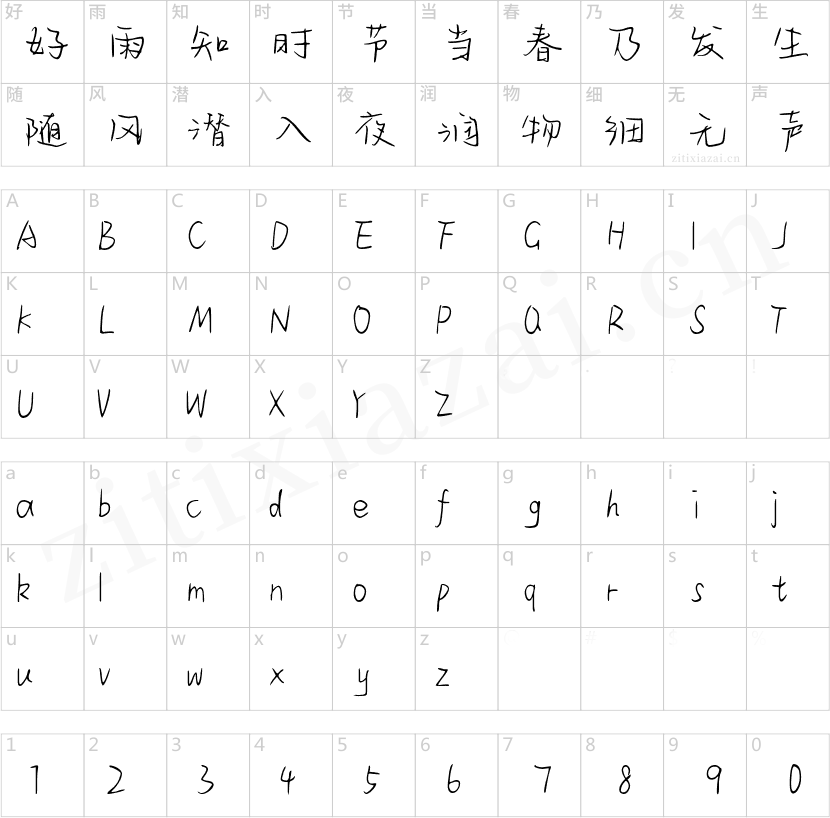
Aa甜桃梦游记
Aa甜桃梦游记,这款字体结构工整、笔画清晰,兼顾美观与易读性,适用于标题、正文、海报、包装、LOGO 等多种场景。字形优雅稳定,风格百搭耐看,适配日常排版与创意设计,让文字呈现更舒适、更具质感。Aa甜桃梦游记一笔一画,皆是细节,以均衡的比例、流畅的线条打造舒适视觉体验,字形端正大气,风格简约现代。无论是商业设计、品牌宣传还是日常排版,都能轻松驾驭,让文字更有格调与力量。Aa甜桃梦游记字体下载。
Aa甜桃梦游记字体
Aa甜桃梦游记是一款非常具有艺术性的字体,它的设计灵感来源于对古典艺术的研究,同时又融入了现代字体设计的元素。字形优美,笔画粗细变化自然,给人以大气、典雅的感觉。Aa甜桃梦游记是一款既传统又现代的字体,它的设计充满艺术感,美观大方,实用性也非常强。无论是对于设计师还是对于普通读者来说,都是一种非常不错的字体选择。Aa甜桃梦游记适合用于具有艺术感的场合,比如海报、宣传单张、书籍封面等。由于其字形流畅且具有动态感,也适合用于大量的文本排版,如报纸、杂志等。